K-콘텐츠의 일본 진출 돕는다… 산돌, 폰트 기업 모토야와 맞손
엄선된 일본어 폰트 100종으로 글로벌 콘텐츠 제작 지원
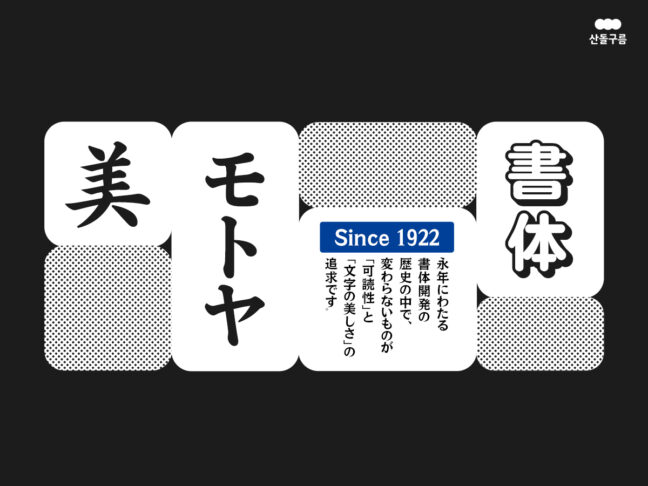
콘텐츠 크리에이터 플랫폼 기업 산돌이 자사의 폰트 플랫폼 산돌구름에 100년 전통의 일본 폰트 브랜드사 모토야(MOTOYA)가 입점했다고 12일 밝혔다.
모토야 입점을 통해 기존 일본어 폰트가 필요했던 국내 사용자는 해당 폰트 구매 시 일본 사이트에서 직접 폰트를 찾아 결제하던 번거로운 과정을 대신, 산돌구름에서 국문 서비스로 편리하게 이용할 수 있다.
모토야는 1922년 활자 제조 판매로 창업한 일본의 전통 폰트 기업이다. 일본의 유명 서예가의 명필을 바탕으로 제작한 모토야 신카이쇼(MotoyaSinkai, モトヤ新楷書)의 개발을 주도했다. 최근에는 깔끔한 디자인으로 가독성뿐만 아니라 시인성까지 고려한 현대적 폰트를 개발해 ▲인터넷 지도 사이트 ▲차량용 기기 ▲의료 및 정밀 기기 등 다양한 디지털 환경에 맞는 폰트를 서비스하고 있다.
이번에 입점된 모토야의 브랜드 상품은 엄선된 일본어 폰트 100종으로 구성됐다. 폰트는 일본의 대표 일간지 닛케이 신문과 산케이 신문에 적용돼 유명한 ▲모토야신문명조(MotoyaNewsMモトヤ新聞明朝) 일본 안드로이드 기본 폰트 ▲모토야시다(MotoyaCedar,モトヤシーダ ) ▲모토야마루베리(MotoyaMaru, モトヤマルベリ) 넥슨의 ‘도미네이션즈 문명창조’에 적용된 ▲모토야아폴로(モトヤアポロ, MotoyaAporo) 등이 포함됐다.